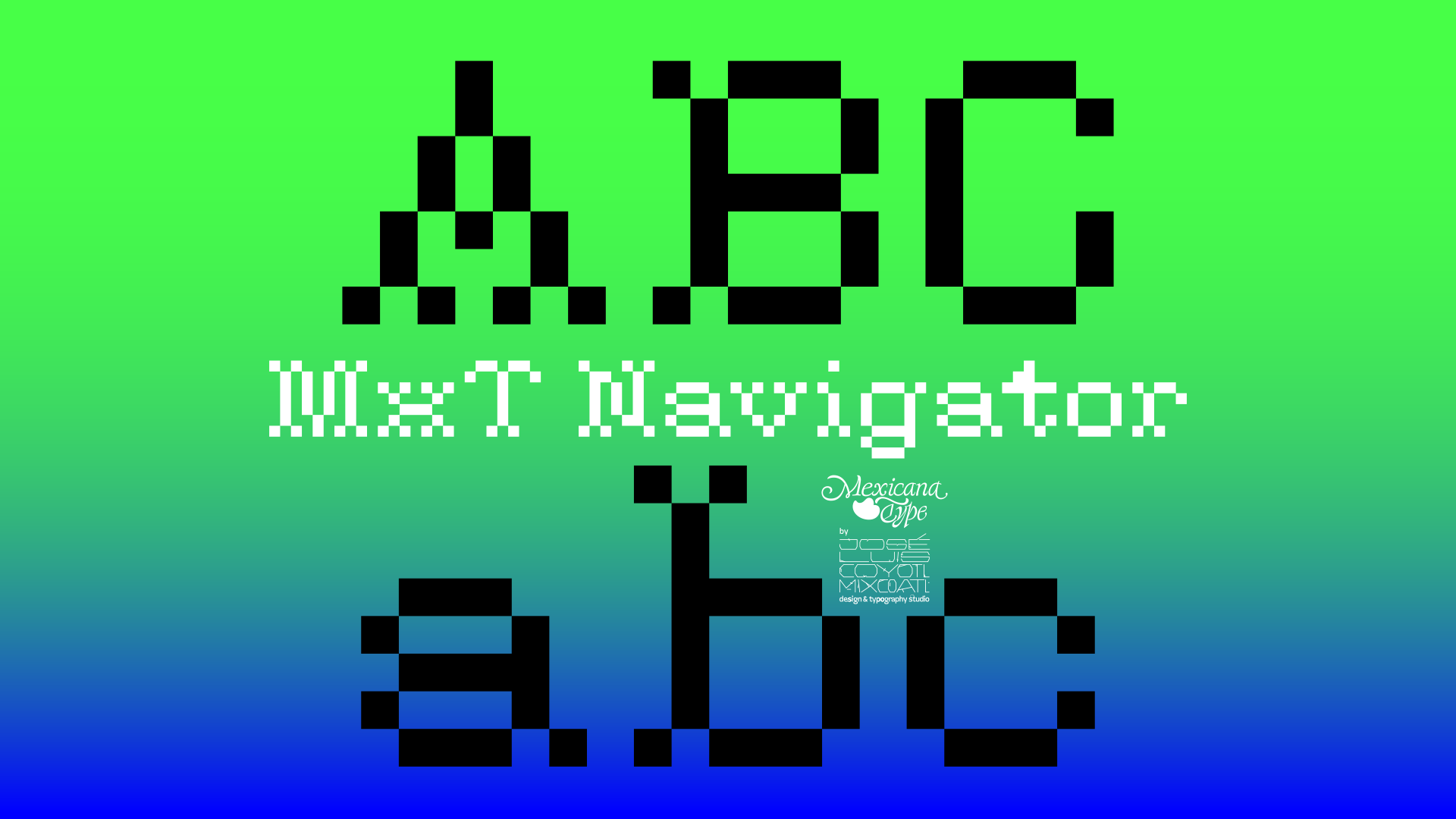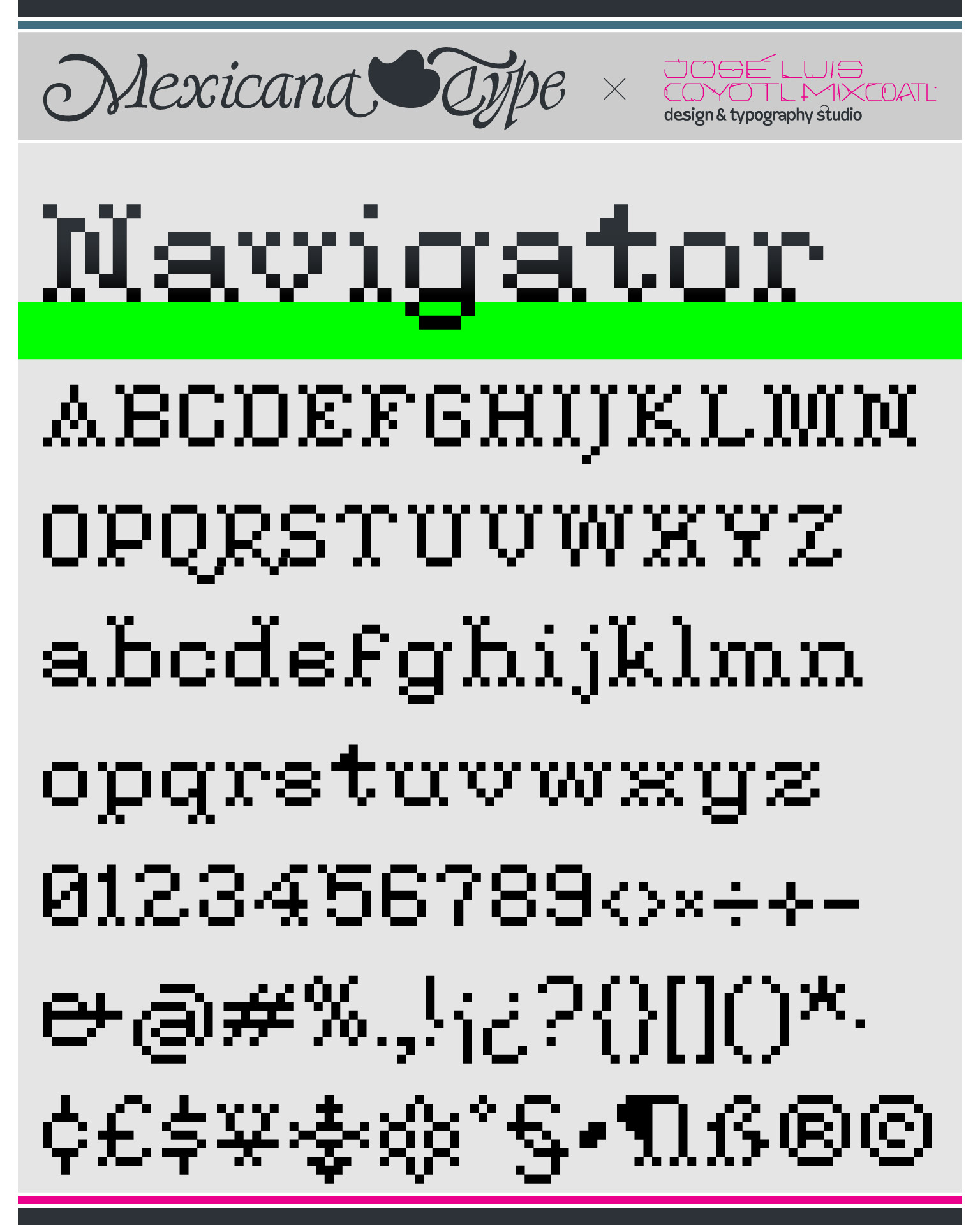
MxT Navigator es tipografía modular y estilo old west unilineal pero con un sistema modular basado en bits o pixeles para cuerpos de texto pequeño para pantalla. Diseñada en base a la estructura tradicional de una romana, construída sobre una base de un módulo cuadrado y una retícula en repetición de esta.
Fue también una colaboración para la revista española de diseño NEO2.